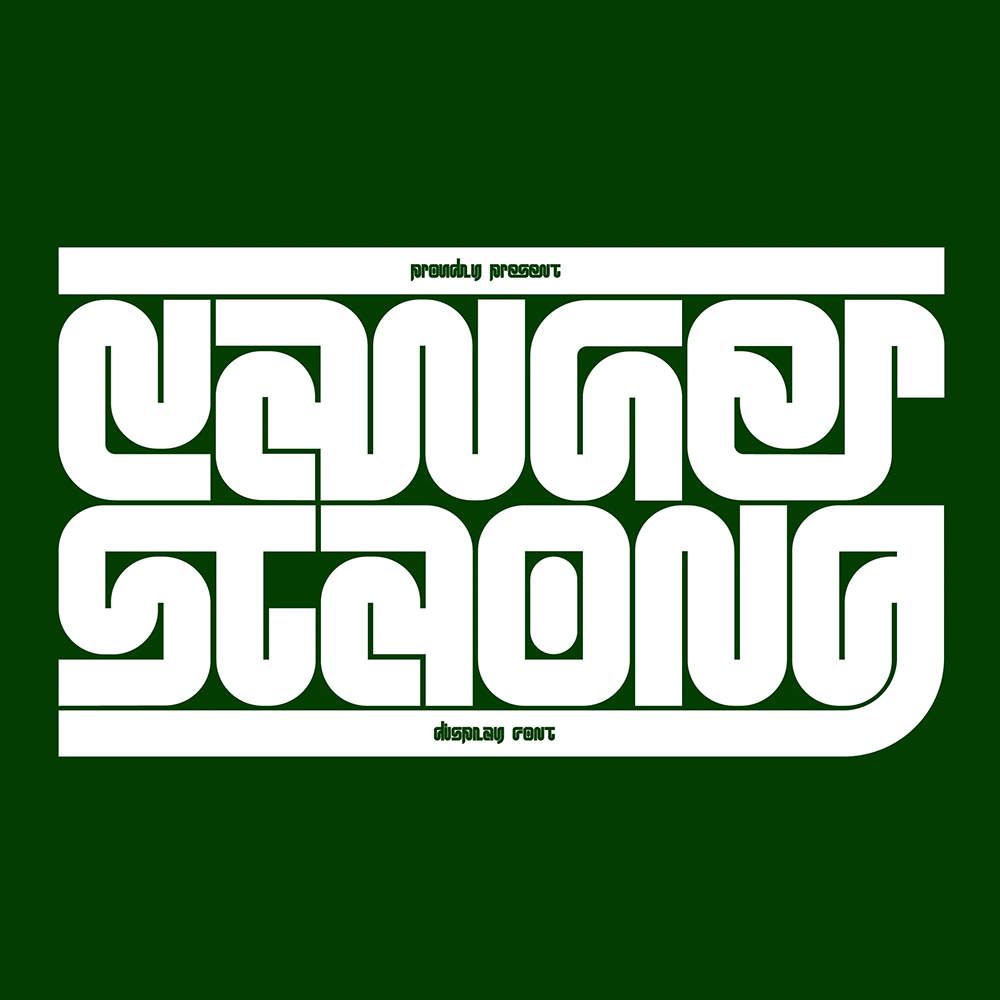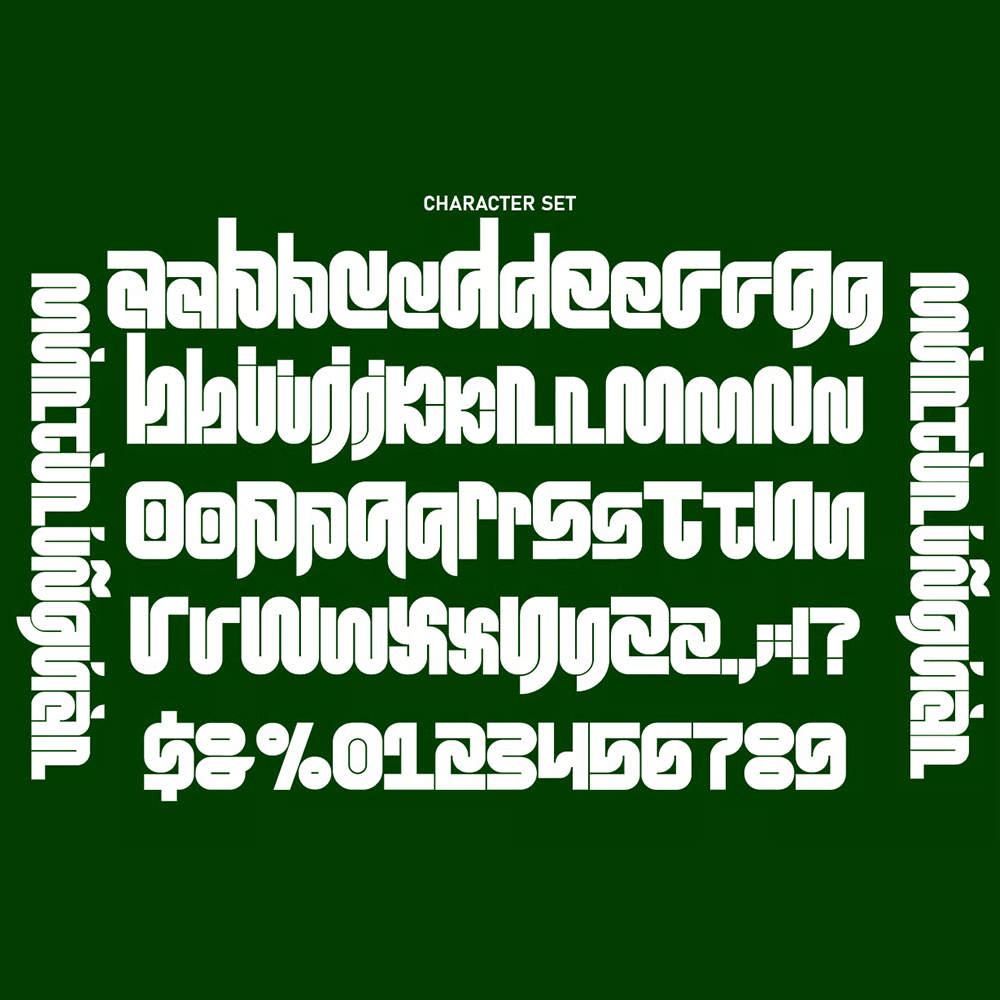
فونت پرمیوم و انگلیسی Canger Staong Font دارای اتصالات منحنی مانند لوله است. از این فونت میتوان در طراحیهای مدرن و معاصر استفاده کرد و برای استفاده در رسانههای متنوعی مانند استیکر، پوستر، جلد، تایپوگرافی و سایر رسانههای دیجیتال مناسب است.